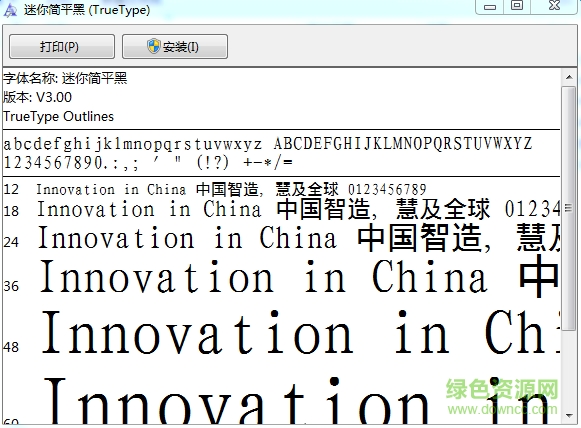
jpinhei是什么字體?jpinhei是一款迷你簡(jiǎn)平黑字體,筆畫粗細(xì)勻稱,筆觸細(xì)膩,簡(jiǎn)潔大氣,常常用于文章的批注或標(biāo)語中,喜歡的小伙伴快來下載吧!
黑體又可細(xì)分為:粗黑、超粗黑(特黑)、大黑、細(xì)黑、美黑、宋黑、水黑、藝黑、氈筆黑、平黑等類型。